- Buka peramban dan kunjungi situs messletters.com
- Ketikkan tulisan yang ingin ditampilkan dengan fon dom Jatim pada bagian 'Enter your text here'
- Gulir ke bawah untuk menemukan teks yang di-generate. Pilih fon 'Carrier' atau 'Carrier II'
- Klik tombol 'Copy' di bagian kanan bawah boks hasil generate teks
- Tempelkan di ruang obrolan, bio Instagram, WhatsApp, atau media sosial lain. Bisa juga digunakan untuk membuat Story, lho.
2 Cara Membuat Font Dom Jatim yang Viral di Medsos
Seorang pengguna X membagikan tangkapan layar yang memuat obrolan melalui direct message Instagram. Bukan isi obrolannya yang membuat warganet heboh, melainkan font estetiknya. Tampilan font tersebut berbeda dan unik, tidak seperti huruf kebanyakan.
Alhasil, banyak yang ingin me-remake atau mengikuti gaya fon tersebut. Nah, buat kamu yang ingin mengikutinya juga bisa pakai cara membuat font dom Jatim dengan langkah berikut.
1. Cara membuat font dom Jatim menggunakan text generator
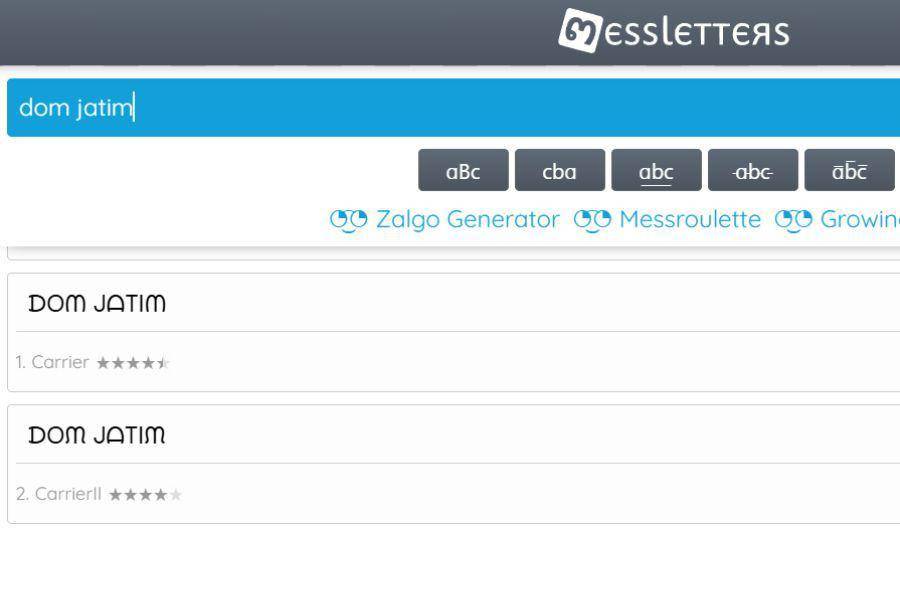
ilustrasi font generator (dok. messletters) Cara pertama ini bisa digunakan saat tidak ingin mengubah fon ponsel secara keseluruhan. Caranya cukup salin teks, lalu manfaatkan text generator.
Nah, hal yang kamu butuhkan adalah situs font generator, contohnya Messletters. Berikut cara menggunakannya:
Dengan font ala dom Jatim ini, kamu bisa membuat obrolan jadi makin menyenangkan. Kalau ingin mengulangi dengan teks atau kalimat berbeda, tinggal ikuti ulang langkah di atas, ya. Agak ribet, sih, tapi seru.
2. Cara membuat font dom Jatim dengan ubah pengaturan ponsel
Ingin menampilkan fon secara permanen pada ponsel? Caranya bisa dengan mengubah pengaturan ponsel. Nantinya, semua menu pada ponsel akan tampil menggunakan fon tersebut
Untuk menerapkannya, bisa ke toko fon yang ada pada perangkatmu. Umumnya, perangkat Android dibekali pilihan fon yang lebih bervariasi sehingga bisa menemukan huruf yang sesuai. Selain itu, bisa juga dengan font changer berikut:
Pada ponsel yang sudah di-root, kamu bisa mengunggah fon sendiri sehingga tidak perlu mencari huruf yang mirip dengan dom Jatim. Untuk menerapkannya, cukup akses situs DaFont.com, lalu cari dan unduh fon bernama Eastman Grotesque versi alternative regular.
Cara membuat font dom Jatim yang viral di media sosial terhitung cukup rumit. Namun, menarik dicoba untuk seru-seruan.